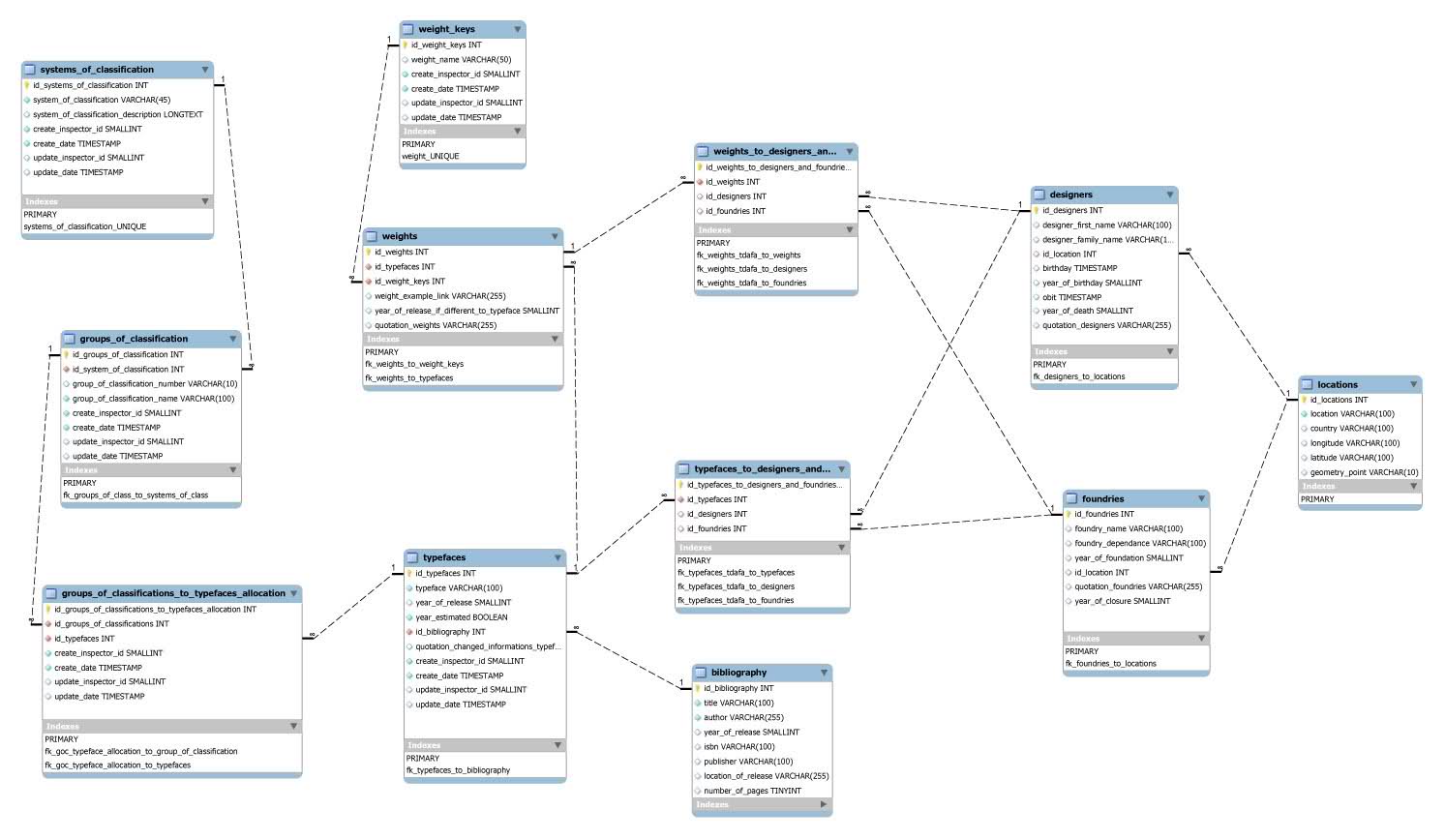
[Global Type] Abfrageschema
Gern möchte ich Euch ein Diagramm zur Diskussion vorwerfen. Es dient dazu, den bestehenden Datenbestand zu erweitern und soll in HTML-Formularen umgesetzt werden. Die Einträge landen dann in einer temporären Tabelle, bis sie einer der Inspectors freischaltet und damit allgemein zugänglich macht.
Sieht für mich auf den ersten Blick schlüssig aus.
Was vielleicht etwas zu kurz kommt (was aber immer ein organisatorisches Problem darstellen kann) ist das Thema der Familie/Sippe und in Folge dann die Einordnung in DIN.
Beispiel Thesis: Slab, Mix, Sans und Antiqua ... das sind 4 Familien in einer Sippe. Diese Gruppierung sollte meiner Meinung nach irgendwo möglich und ersichtlich sein, da sie für den Anwender nützlich ist (sichere Bank beim Schrift-Mischen), und dem Entwurfsgedanken aller Sippen/Familienmitglieder zugrundeliegt.
Vielleicht lässt sich das über eine Funktion "Familie X ist originär mit ... verwandt" verknüpfen?
Meines Wissens die erste Schriftsippe mit Angehörigen aus unterschiedlichen Schriftgruppen war doch die Corporate A (Antiqua), E (Egyptienne) und S (Sans) von Kurt Weidemann, oder nicht? So etwas sprengt einfach die DIN. Oder es gibt eine Mehrfachzuordnung wie bei den Fontformaten jetzt schon. Bei der ATypI gibt es übrigens eine neue Special Interest Group zur Schriftklassifikation. Danach werde ich mich dann richten.
Am besten dazu mit Indra Kupferschmid beraten. Das ist ihr Spezialgebiet.
Ich stimme aber zu: Die Einordnungen in Sippen und Klassifikationen ist das eigentlich knifflige an jeglichen Schriftdatenbanken. Das Datenbank-Schema muss dies von Anfang an berücksichtigen – im laufenden Prozess ist es dann schwer dies noch umzusetzen.
... Corporate A (Antiqua), E (Egyptienne) und S (Sans) von Kurt Weidemann, oder nicht? So etwas sprengt einfach die DIN. Oder es gibt eine Mehrfachzuordnung wie bei den Fontformaten jetzt schon.
Meines Wissens nach war das die erste, bei der drei Schriftfamilien aufeinander abgestimmt waren und den selben Namen (+Zusatz) trugen.
Inzwischen gibt es das ja recht häufig – somit ist die Anforderung, das systematisch zu erfassen einfach gegegeben und die DIN wird der Realität nicht mehr gerecht.
Und auch davor waren schon einige Schriften auf gemeinsame Verwendung hin abgestimmt (z.B. bei Frutiger), wenn auch noch nicht mit vollem Konzeptgedanken und Benennung – ob man das aber berücksichtigen kann/soll, ist schon die nächste Frage.
Für die Datenbank hieße das grob umrissen: jeder Schrift(familie) können beliebig viele "konzeptionell verwandte" Schrift(famili)en zugeordnet werden. Es gäbe also nicht nur einen hierarchischen Baum mit Ästen, sondern auch Querverbindungen zwischen den Ästen – oder aber eine mehrdimensionale Matrix, in die jede Schrift einsortiert ist. Die Dimensionen könnten dann einerseits die DIN-Kritierien sein, aber eben um andere, vielleicht zeitgemäßere Perspektiven ergänzt sein (Matrix Willberg, ...).
Aber: Damit steigt auch der Aufwand beim Einstellen signifikant an!
Die Dimensionen könnten dann einerseits die DIN-Kritierien sein, aber eben um andere, vielleicht zeitgemäßere Perspektiven ergänzt sein (Matrix Willberg, ...).
Aber: Damit steigt auch der Aufwand beim Einstellen signifikant an!
Wir haben die Möglichkeit vorgesehen, alternativ zur DIN auch weitere Schriftenklassifikationen einzuführen. Insbesondere interessiert es mich, wie sich die Special Interest Group Type Classification der ATypI entwickeln wird. Danach werde ich mich auf jeden Fall richten. Wie Du im ERM an den drei Entitäten ganz links sehen kannst, ist die Option dann eingebaut.
Hm – das Bild war zu breit. Hier das ERM als PDF. Es geht um die drei Entitäten links außen – systems of classifications, groups of classifications to typefeaces allocations.
Das besagte Problem steckt da schon drin. Den Klassifikationsgruppen werden »Schriftfamilien« zugeordnet. Aber was ist nun, wenn die Familienmitglieder zu anderen Gruppen gehören?
In diesem System müsste zwanghaft jede Unterfamilie selbst zu Familie erklärt werden.
Was ich rein datenbanktechnisch auch nicht verstehe, sind die Zuordnungstabellen. Warum gibt es da mehr als 2 Einträge? Also weights_to_designers_and_foundies und typefaces_to_designers_and_foundries. Das provoziert auch Probleme, wenn einzelne Datensätze nicht in dieses Schema passen. Ganz zu schweigen von wiedersprüchligen Angaben, die in so einer Tabelle möglich wären.
Am besten dazu mit Indra Kupferschmid beraten. Das ist ihr Spezialgebiet.
Ich stimme aber zu: Die Einordnungen in Sippen und Klassifikationen ist das eigentlich knifflige an jeglichen Schriftdatenbanken. Das Datenbank-Schema muss dies von Anfang an berücksichtigen – im laufenden Prozess ist es dann schwer dies noch umzusetzen.
Ich dachte mir, dass schlicht Verzweigungen möglich sind. Nach dem Prinzip: Schrift xy kommt in Klassifikation A in die Schublade m, bei Klassifikation B in die Schublade n.
So ein Datenbank-Modell ist auch nicht einfach zu verstehen. Kein Wunder, dass du da kaum Feedback bekommst. Eigentlich musst du erst alle theoretischen Möglichkeiten mit Typo-Leuten durchsprechen und dann mit einen Datenbank-Experten diese Umsetzen. Die zwei Welten sind naturgemäß schwer zu vereinen. ;-)